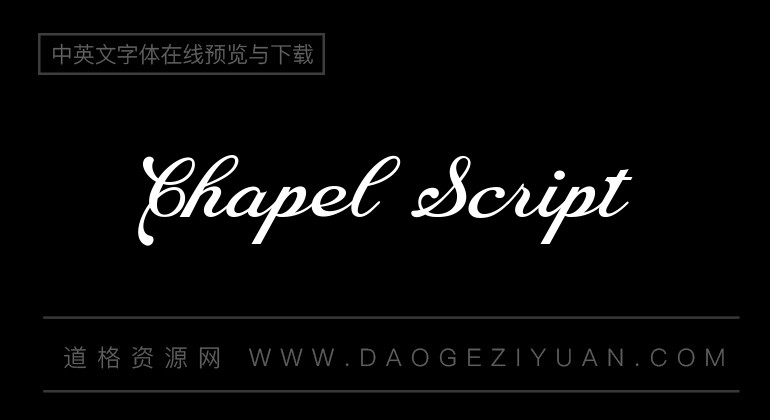
Chapel Script
Chapel Script是一款由英国设计师Lesley Barnes创作的精致字体。它具有温柔、柔和、优雅的特点,是一款细腻的手写字体,适合用于卡片、海报、婚礼邀请函、T恤或任何其他艺术创作。Chapel Script字体拥有自然的节奏和流畅的线条,它的设计受到20世纪50年代的美式字体的启发,并结合了更现代的设计元素。Chapel Script字体也可以用来制作精美的拼图效果,以及更多的设计元素。
Chapel Script是一款非常不错的手写艺术字体,具有很好的视觉感,适合于文化类的宣传设计、商业类品牌的广告和产品包装设计以及个性化文字排版等较多场景。